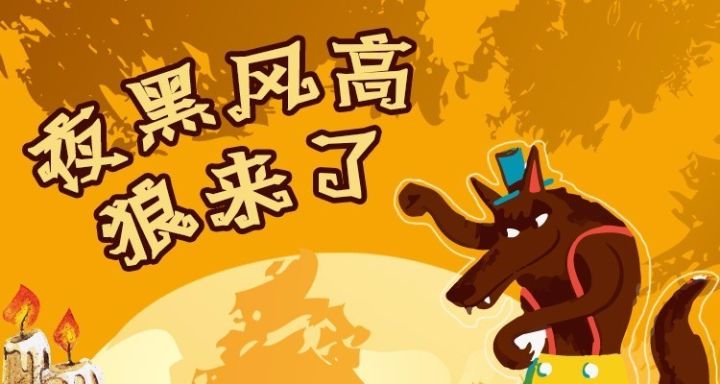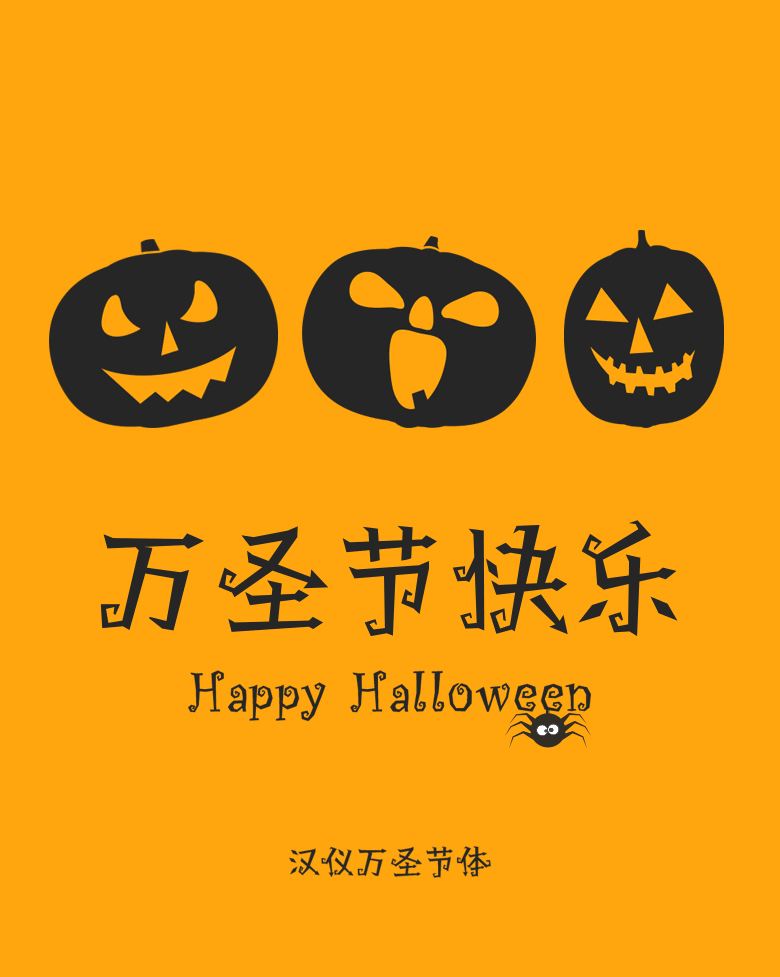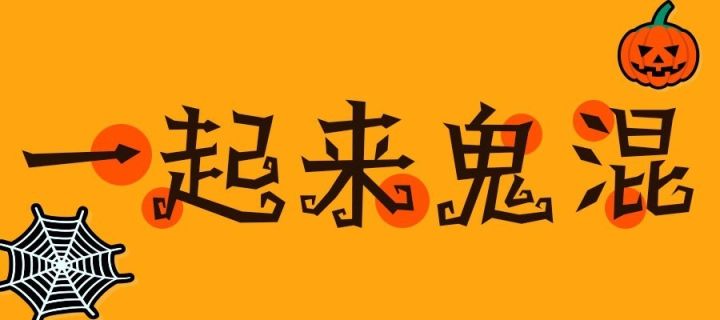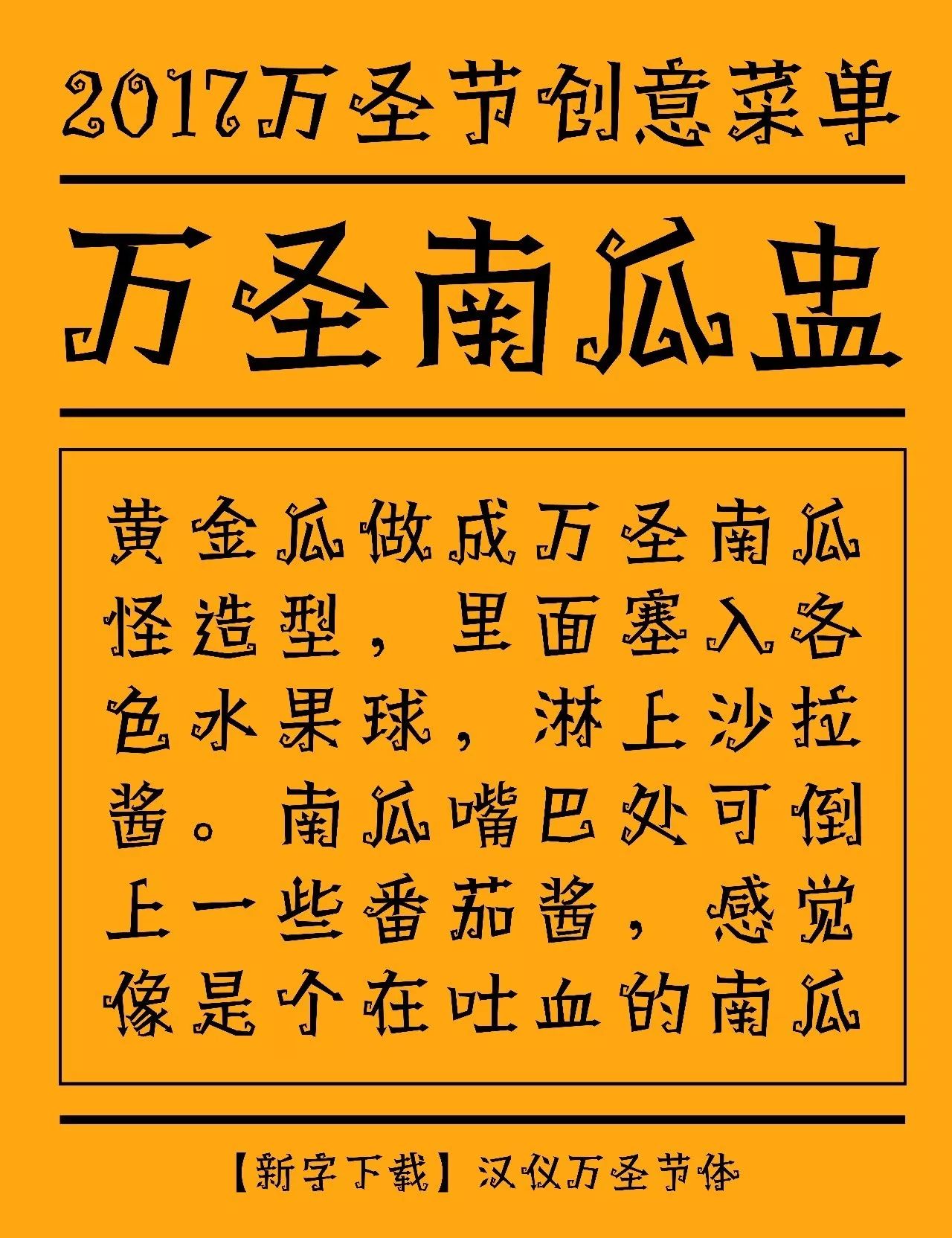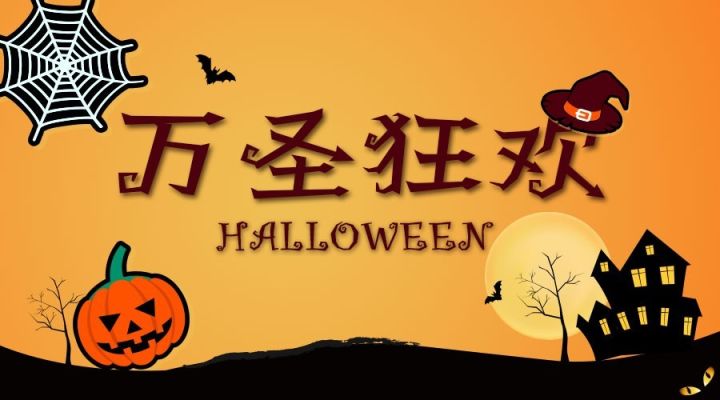
适合万圣节的字体大全,包含汉仪万圣节体
今年的万圣节即将到来
没有南瓜灯🎃、没有糖果🍬、没有化妆舞会💃
难道又要这样平淡的度过?
👿
开玩笑
这怎么会影响小编那颗想“鬼混”的心
产品经理:你这个节日字体不太好
再改一下 !
市场经理:万圣节的banner字太丑
再换一个!!
运营主管:节日文案好了图片的字
随便配一个!!!
你们一群龟儿子等老子做甲方虐死你们
💣💥
以为这就能阻拦的了我
手里没款匹配的节日字体
怎么好意思混迹设计圈
就是这样的简单粗暴
这就是汉仪新发布的
🎉 汉仪万圣节体 🎉
笔画延伸的造型,像是魔法树妖的爪子
似利箭的笔形,为字型增添了魔幻色彩
轻松的字型结构不规则的部件比例
让这款字变的更加轻松活泼
种种特点结合绝对让你感受到
万圣节那诡异魔幻的气息~
邪恶的小编能告诉你
万圣节我来喽~